Markus Hanzer »Genesis«, kostenloses iBook [Update]
Wahrscheinlich ist es das erste iBook im Selbstverlag, das von einem professionellen Gestalter mit der neuen Macintosh-Software iBooks Author erstellt wurde, die Apple vor 2 Wochen vorgestellt hat … Der österreichische Designer und mehrfache TYPO-Berlin-Sprecher Markus Hanzer hat es gestern veröffentlicht. Unter dem Titel »Genesis« setzte er sich auf der TYPO Berlin 2011 mit den Veränderungen in seinem Beruf auseinander. Der viel beachtete Vortrag lieferte nun den Inhalt für sein kostenloses e-Book, das im iTunes-Store zum Download bereit liegt.
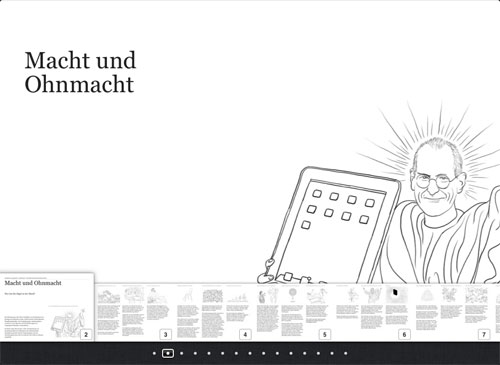
Das Buch beleuchtet die unterschiedlichen Vorstellungen, die sich im Laufe der Geschichte über den Mensch als Gestalter entwickelt haben und fragt danach, welche dieser Ansätze noch von Bedeutung sind. In jedem Diskurs über Gestaltung taucht früher oder später die Frage auf : Wer hat die Zügel in der Hand? Wer hat die Welt in ihrer uns erfahrbaren Form geschaffen? Ist das Werk gelungen? In welchem Rahmen sind Veränderungen denkbar und wer hat das Recht ein Urteil zu fällen?
Je mehr Gestaltungsarbeit sich von traditioneller Handarbeit entfernt, indem wir mit Programmen und vorgefertigten Templates und Designelementen von der Stange arbeiten, desto komplexer wird die Rechtslage, die uns vorgibt, wie weit unsere Handlungsspielräume noch reichen, welche Rechte den so genannten Urhebern eingeräumt werden, wer, was als sein geistiges Eigentum bezeichnen darf, und somit auch, welche Schranken und Grenzen der Gestaltung gesetzt werden. Wer hat das Recht die Welt umzugestalten und wer darf wann andere zur Kasse bitten, wenn diese vorgefundene Gestaltungselemente benutzen wollen?
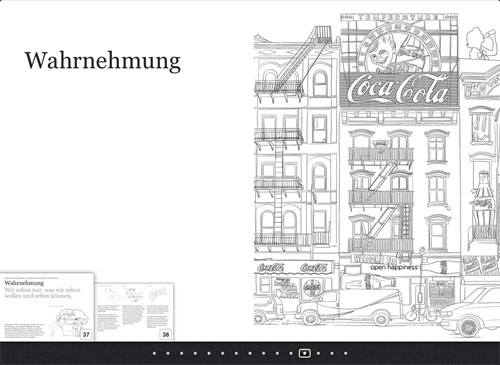
Es zeigt sich, dass Gestaltung nach wie vor der gemeinschaftlichen Konstruktion eines Weltbilds dient. Beim Design werden zentrale Fragen verhandelt, zum Beispiel wie wir zu unserer Umwelt stehen, wie wir unser Zusammenleben ordnen und welchen Zielen wir unsere Lebensenergien widmen? Es geht gar nicht mehr darum, jeden denkbaren Raum mit Zeichen zu füllen, sondern einen Raum zu schaffen, in dem sich Zusammenleben entfalten kann. Oder wie die von Markus Hanzer zitierten Hans-Joachim Gögl und Josef Kittinger meinen: »Veränderung führt über das Erlebnis der Alternative. Wandel benötigt sinnlich erfahrbare Modelle anderer Realitäten; Prototypen einer anderen Wirklichkeit. Denn wir verwandeln uns in das, was wir betrachten, da die Energie der Wahrnehmung folgt. Wir sind somit verantwortlich für unsere Aufmerksamkeit.«
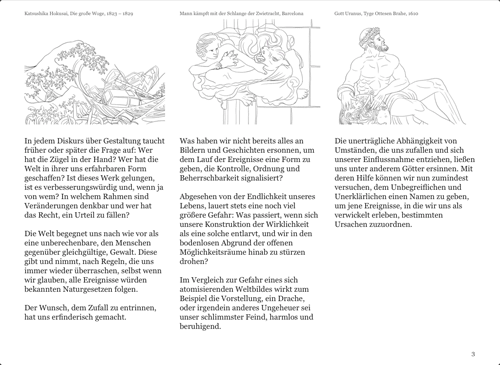
Fazit: Das in den letzten Jahrzehnten gewachsene Heer an Gestalterinnen und Gestaltern wird dringend gebraucht, sollte es gelingen, dass jene die Hilfe suchen, diese auch finden.
Ich sprach mit Markus Hanzer über die Produktion seines e-Books:
Fontblog: Markus, wie hast Du das e-Book produziert?
Hanzer: Ich habe die Datei mit iBooks Author generiert … und – um ehrlich zu sein – sogar eines der angebotenen Templates benutzt.
Wie aufwendig war das für dich?
Nach dem ich mit Keynote sehr vertraut bin, bewege ich mich hier auf gewohntem Terrain. Unmittelbare Benutzung ohne jede Gebrauchsanweisung ist überhaupt kein Problem. Das Programm macht vielleicht Designer die sich primär mit QuarkXPress und Indesign beschäftigen nicht sehr glücklich, da Feinjustierungen in diesem Umfang nicht vorgesehen sind. Aber so schnell etwas veröffentlichen zu können, finde ich revolutionär.
Was kostet die Software?
Das Programm ist kostenlos, der Vertrieb meines Buches über den iTunes-Book-Store ebenso.
Was hat Apple davon?
Apple will damit jede Menge Publikationen in seinen Store spülen und damit auch den Verkauf des iPads voran treiben. Die Möglichkeiten die das iPad bietet sind durchaus berauschend und wir stehen ja hier absolut noch in den Anfangstagen.
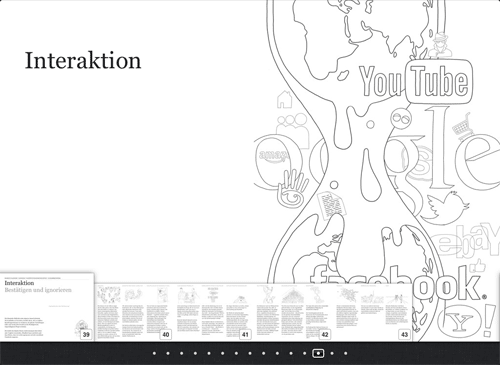
Wo werden wir demnächst iBooks sehen?
Vor allem im Bildungsbereich, in dem Apple auch mächtig Gas gibt, sehe ich einschneidende Möglichkeiten Unterricht spannender, lebendiger, einprägsamer und individueller zu machen.
Brechen auch für Autoren neue Zeiten an?
Ob es für Autoren auf diesem Weg leichter wird, ein Publikum zu finden, sei dahingestellt … Die Zeit wird es weisen.
Hat Apple Dein Buch geprüft?
Ich habe keine Ahnung ob Apple das Buch geprüft hat. Sie haben mit mir in keiner Weise kommuniziert. Ich habe auch kein Bestätigungsmail oder sonst ein, wie immer geartete Nachricht bekommen.
Wie lange dauerte die Freigabe?
Ein paar Stunden. Falls man bei Apple in die Datei schaut, was ich annehme, hängt die Bearbeitung sicher davon ab, wie viele Uploads in einem bestimmten Zeitraum erfolgen.
Neue Volksbank-Spots setzen auf Geschriebenes
Vor genau zwei Jahren habe ich hier im Fontblog die  typografische »Was-uns-antreibt«-Printkampagne der Volksbanken Raiffeisenbanken vorgestellt: Schriften sind Schauspieler des geschriebenen Wortes. Auch die neuen Werbespots inszenieren den besonderen, auf die Wünsche der Kunden und Mitglieder bezogenen Ansatz der genossenschaftlichen Banken, erneut mit dem geschriebenen Wort.
Nachdem sich die Schöpfer der  erfolgreiche »Antriebskampagne« häufiger mit Nachahmungen konfrontiert sahen, musste freilich eine neue, eigenständige Stilistik gefunden werden, die in den Grundelementen mit der alten erkennbar verwandt ist. Nun baut die Kampagne nicht mehr auf fertige Satzschriften, sondern die Wörter bilden sich aus Handschriften, Objekten, Stop-Motion-Blumenarrangements oder aus Gebasteltem. Die Spots werden ab heute in privaten und öffentlichen Sendern geschaltet.
Jürgen Siebert: Die Restriktionen zeigten sich bereits beim FontBook 4, das 2006 erschien. Die Menge der darzustellenden Schriften war gegenüber der vorherigen Auflage um 30 Prozent gestiegen, das ergab 32.000 Schriftmuster von 90 Foundries (plus 25 %). Hinzu kamen 100.000 neue lexikalische Angaben. Um diese Informationsmenge in einen Band zu packen, mussten wir schmerzhafte Kompromiss eingehen. Zum Beispiel schrumpfte die Darstellung eine FF Meta-Familie von drei Seiten im FontBook 3 (1998) auf eine Seite im FontBook 4, und dies obwohl die Schrift von 26 Fonts auf beachtliche 300 gewachsen war. Dies konnten wir nur erreichen, indem wir die Schnitt-Varianten Reg / SC / LF / EXP / SC LF / SC EXP auf vier Zeilen Text in Lesegröße zusammendampften … nicht gerade benutzerfreundlich. Trotz der Abstriche  ließ sich nicht verhindern, dass das FontBook 4 am Ende auf eine Rückenbreite von 6,5 cm anwuchs und über 3 Kilo wog. Der Buchbinder hatte seine liebe Mühe und musste nach der Prüfung einer Testcharge noch mal von vorn anfangen, weil der Buchblock bereits beim Anheben aus dem Umschlag herausbrach. (weiterlesen …)